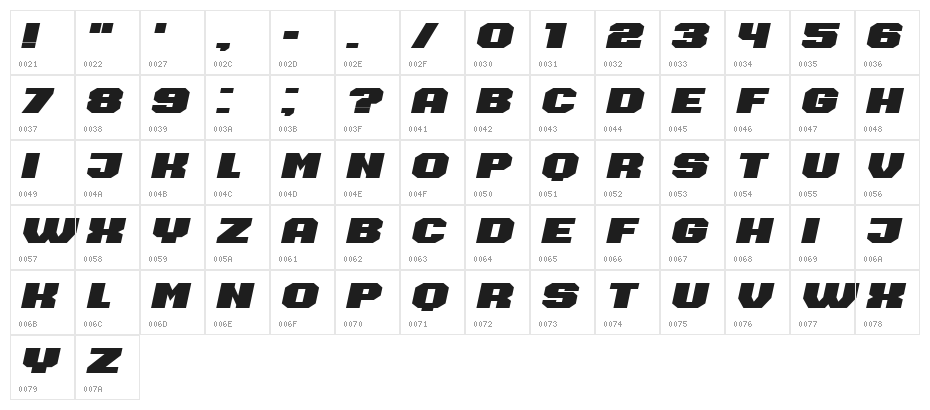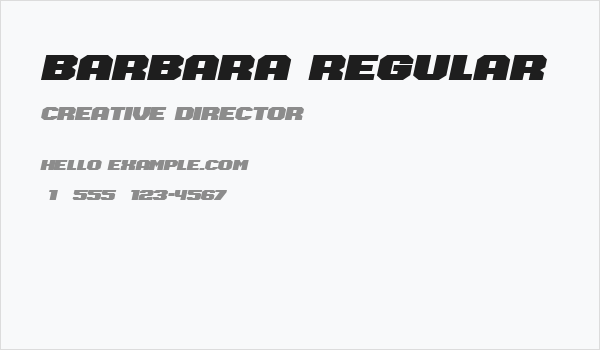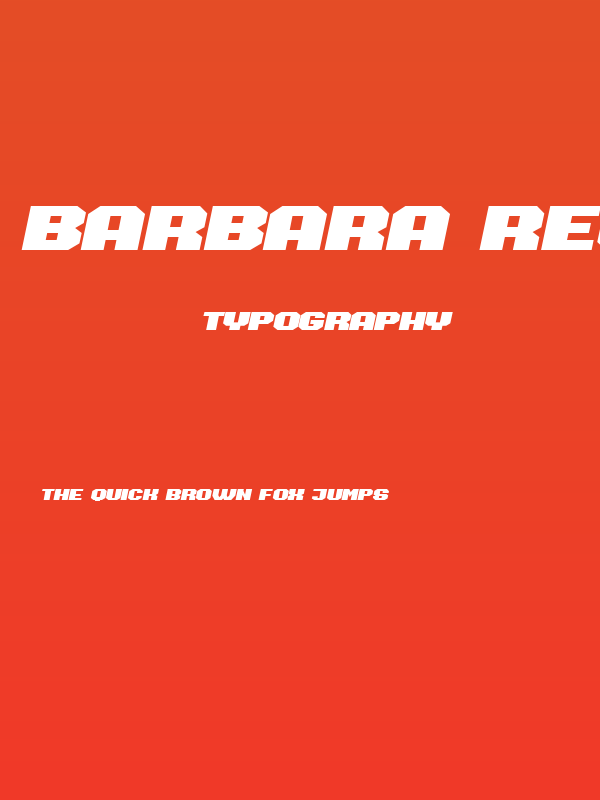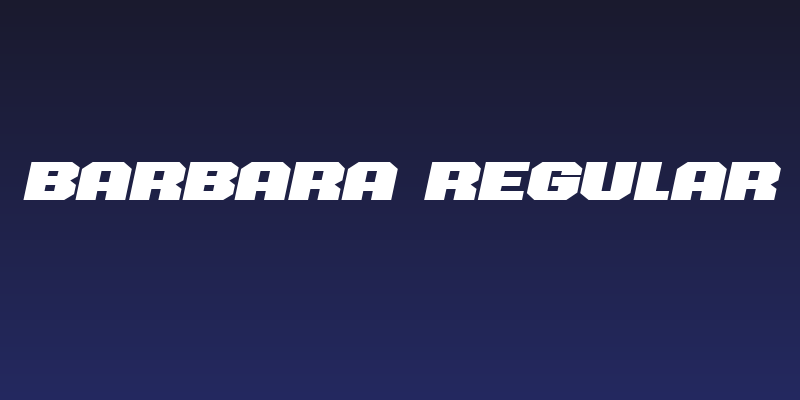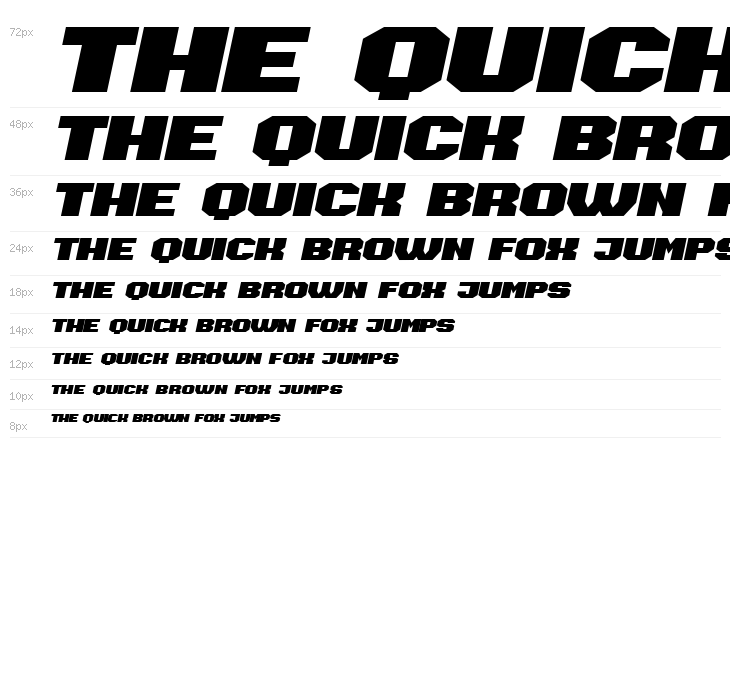
Barbara Regular Font
| Vorgeschlagene Projekte | Ideal for branding, posters, video game graphics, and any project requiring a strong, modern aesthetic. |